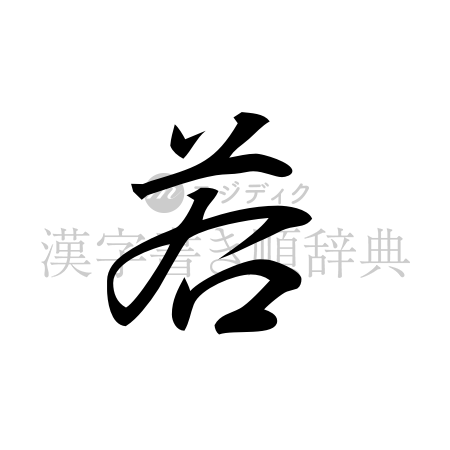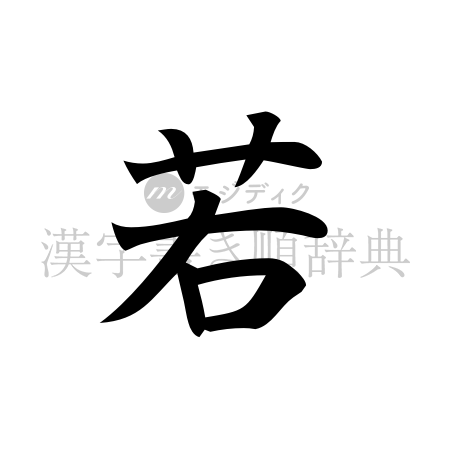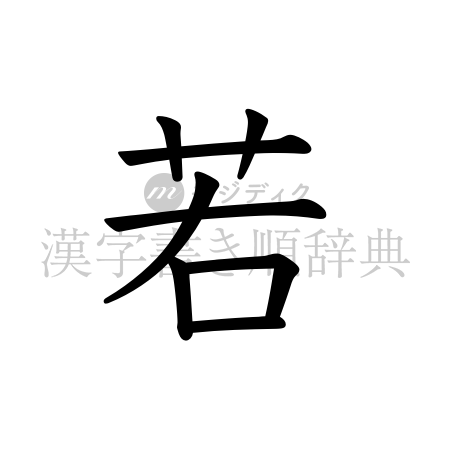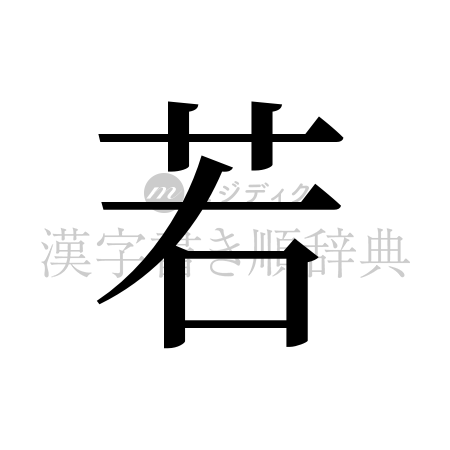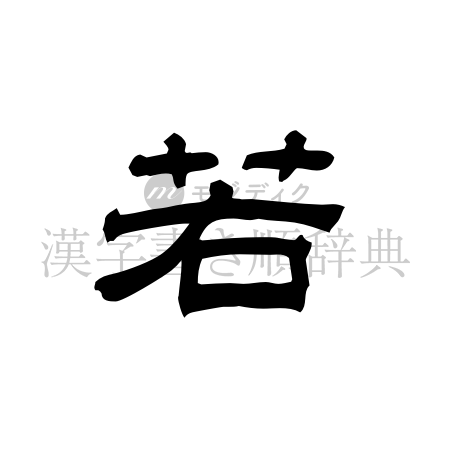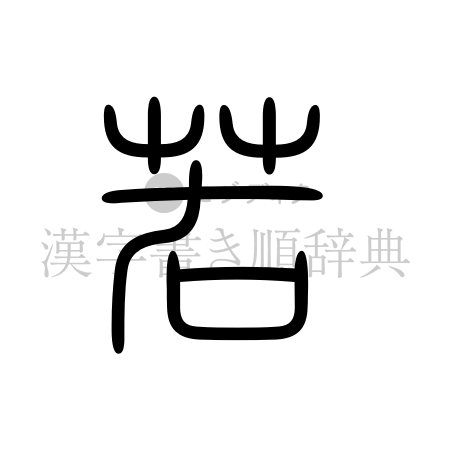
漢字「若」(くさかんむりに右)の書き順・読み方・意味・部首・画数
「若」の書体
• 若の書体「ゴシック体」のイメージ
• 若の書体「明朝体」のイメージ
• 若の書体「教科書体」のイメージ
• 若の書体「楷書体」のイメージ
• 若の書体「行書体」のイメージ
• 若の書体「草書体」のイメージ
• 若の書体「隷書体」のイメージ
• 若の書体「篆書体」のイメージ
「若」の意味
• 若い。
• もし。
• ごとし。
• しなやか。
• 従う。
• 似ている。
• 若しくは。
• 何か。
「若」の意味の英訳
漢字は1文字で多様な意味を持ちますが、「若」を英語で表す場合、一般的には young, if, perhaps, possibly, low number, immature などがあります。
「若」の成り立ち・由来
六書分類 象形文字
構造 ひざまずいた人が両手で髪を梳き整える姿を描いた象形
「若」は、ひざまずいた人が両手を挙げて髪を梳き整える姿をかたどった象形文字とされます。髪をしなやかに整えることから「したがう」「なめらか」の意が生まれ、また同音を借りて「もし」「ごとし」の意にも用いられました。「若い」の意味もこの借用によるものです。なお『説文解字』は艸(草)と右からなり菜を選ぶ意とするなど、字源には諸説あります。上部のくさかんむりと下部の口・右は、こうした字形が整えられて現在の形になったものです。
※ 字源には髪を整える人とする説と、菜を選ぶ意とする『説文解字』の説などがあり諸説あります。
「若」の構成部品
「若」は上に「艹(くさかんむり)」、下に「右(みぎ・ウ)」を組み合わせた漢字です。